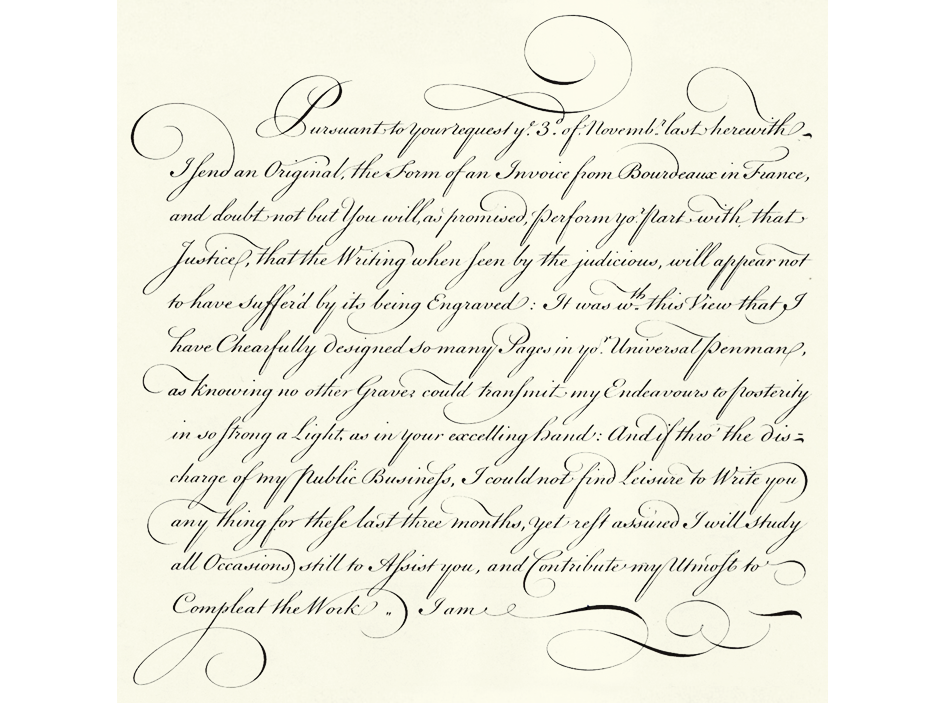
Шрифт, имитирующий рукопись, 6 (шесть) букв
рукописный шрифт — это… Что такое рукописный шрифт?
рукописный шрифт — Шрифт, имитирующий рукописный текст.
В таком шрифте каждая буква как бы переходит в следующую, однако без реального соединения. [http://www.morepc.ru/dict/] Тематики информационные технологии в целом EN cursivecursive type … Справочник технического переводчикаРукописный шрифт — (СКРИПТ) шрифт, выполненный от руки или имитирующий его … Реклама и полиграфия
Рукописный шрифт — Проверить информацию. Необходимо проверить точность фактов и достоверность сведений, изложенных в этой статье. На странице обсуждения должны быть пояснения. Рукописный шрифт (скрипт) шрифт, вы … Википедия
Шрифт Зюттерлина — (нем. Sütterlinschrift, [ˈzʏtɐliːnˌʃʁɪft]) последняя широко используемая форма куррента, немецкого готического курсива … Википедия
Шрифт — набор символов алфавита характеризующихся одинаковыми: характером рисунка; формой: прямой, наклонный, курсив; насыщенностью: светлый, полужирный, жирный; и размером в пунктах.
Шрифт предназначен для восприятия информации людьми и устройствами.… … Финансовый словарьШРИФТ — ШРИФТ, а, мн. ы, ов и ы, ов, муж. Форма письменных или печатных знаков. Печатный, рукописный, рисованный ш. Рисунок шрифта. Наборный ш. (полученный в результате типографского набора). Типографский ш. (комплект литер и других элементов для набора) … Толковый словарь Ожегова
Шрифт — (нем. Schrift, от schreiben писать) графическая форма знаков алфавитной системы письма (См. Письмо). В зависимости от техники воспроизведения Ш. различают след. его основные виды: рукописный, написанный пером или другим инструментами на… … Большая советская энциклопедия
Шрифт — Полуустав Цифры и русские буквы в стиле готического шрифта Шрифт (нем. … Википедия
Рукописный русский алфавит — Русское курсивное письмо Русский курсив специальный рукописный кириллический шрифт.
Начертание букв значительно отличается от типографского шрифта. Русский печатный курсивный шрифт развился под влиянием рукописного. Письмо осуществляется с… … ВикипедияСкоропись (шрифт) — Жалованная грамота великого князя Ивана Васильевича Спасо Преображенскому Соловецкому монастырю (1539) У этого термина существуют и другие значения, см. Скоропись. Скоропись вид … Википедия
Моноширинный шрифт
— (внизу) в сравнении с пропорциональным Моноширинный, или непропорциональный шрифт это шрифт, все знаки (точнее, кегельные площадки знаков) которого имеют одинаковую ширину … Википедия
Шрифт рукописный — Энциклопедия по экономике
III группа — неразборчивый рукописный оригинал с большим количеством поправок, превышающих 50% текста, синька, мелкий типографский шрифт. [c.4]Характеристика работ. Гравирование знаков, надписей различными шрифтами и гравирование несложных рисунков на деталях и изделиях из металла, стекла, пластмасс и других материалов на гравировальных станках различных конструкций и по копиру.
Первые программы распознавания текстов работали по принципу сравнения распознаваемого символа с набором эталонов. Задача разработчиков программы сводилась к выбору критерия похожести распознаваемого символа с одним из эталонов. Если в документе встречался текст набранный другим шрифтом, то начинались проблемы. Такие программы требовали так называемого обучения , то есть предварительного распознавания тестовой страницы и ручного указания, какое изображение имеет каждый символ. Однако современные программы распознавания текстов, используя последние научные достижения в данной области, могут уверенно распознавать символы различных шрифтов, включая напечатанные на матричном принтере и даже рукописные. [c.168]
В средневековой Европе в рукописях использовались разные шрифты в зависимости от типа книг или документов или от того, когда и где была выполнена транскрипция. По этой причине печатники инкунабул использовали различные гарнитуры в зависимости от рукописи, на основе которой они создавали книги. В те дни не было мастеров, специализирующихся на литье шрифтов, поэтому печатникам приходилось создавать штампы самостоятельно или покупать их, или закупать только матрицы для самостоятельного литья шрифта.В результате каждый принтер использовал разные шрифты, и в исследованиях инкунабул эти шрифты используются в качестве доказательства для идентификации конкретного принтера.